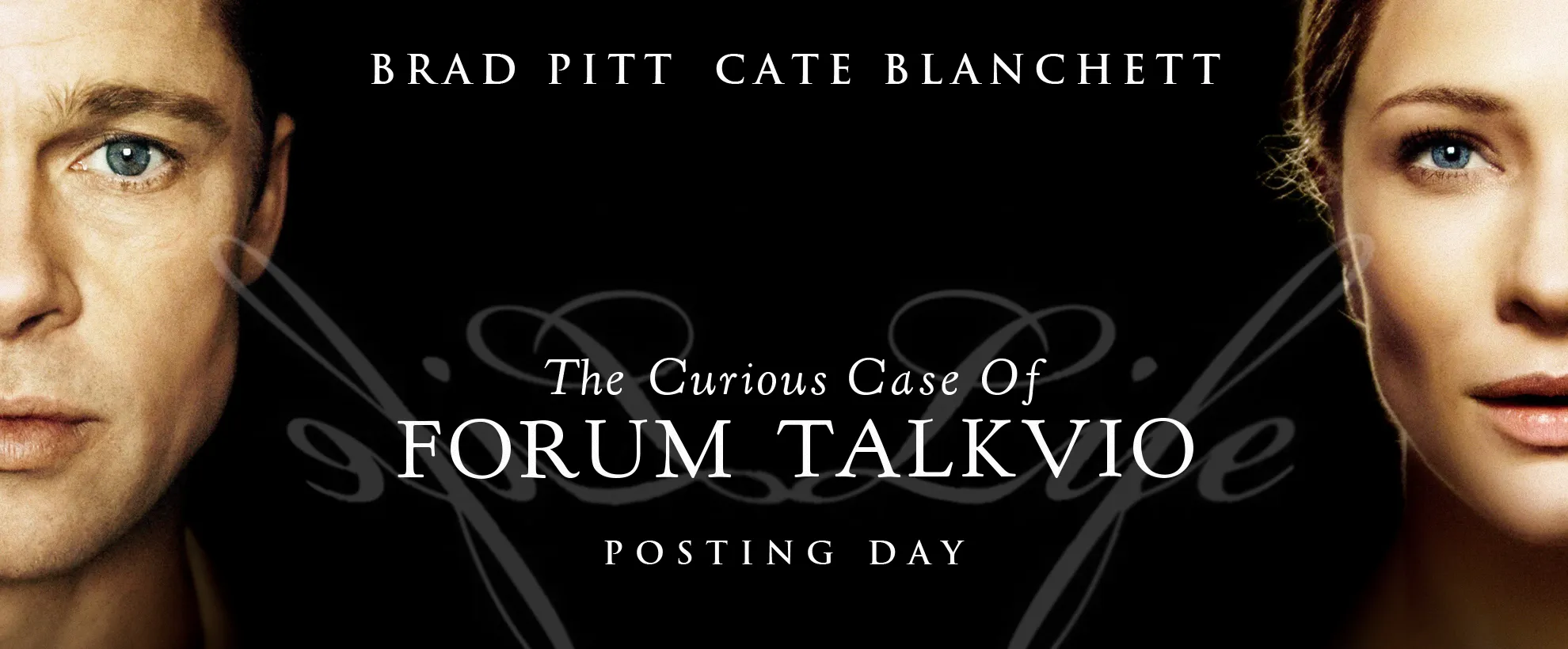
Для промокампании фильма «Загадочная история Бенджамина Баттона» создатели использовали три шрифта.
Для центровой надписи были использованы два написания (Regular и Italic) шрифта LTC Kennerley. А для написания имён актёров, даты выхода и прочих надписей был взят шрифт Trajan.
LTC Kennerley и все его виды – это довольно старый, платный, но достаточно интересный шрифт. Он не предназначен для некоммерческого использования, не поддерживает кириллицу. А большая часть сайтов, которые предлагают этот шрифт бесплатно, подсовывают слегка изменённую копию этого шрифта. Тем не менее он имеет достаточно приятное написание и может использоваться в дизайнерских работах.
Trajan же относительно новый, достаточно популярный полностью заглавный шрифт. Его, насколько я понял, можно использовать в коммерческой деятельности, а также он поддерживает кириллицу. Шрифт ходовой и довольно многозадачный, если постараться с оформлением.